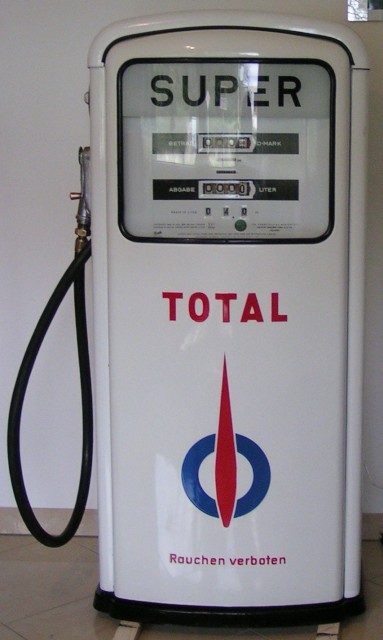
Schriftart altes "Total" Logo von 1955
ich suche die Schriftart vom Schriftzug "Total" der Beispielgrafik im Anhang.
Es handelt sich um eine Zapfsäule, die noch ca. im Jahr 1955 verwendet wurde.
Evtl. ist der Schriftzug auch eine Eigenkreation...
Total hat damals keinen waagerechten Schriftzug verwendet, daher ist der Schriftzug nur eine Anlehnung ans Logo.
1954
July 14 (Bastille Day) is chosen as the launch date for the "Super Carburant Total" brand. The first TOTAL logos emphasize its French nationality, with the name in red letters against a white background between two blue triangles. Marketing operations expand, and Total-branded products are introduced in different markets
1955
A gas pump logo expands on the French theme, with a red flame on a blue circle against a white background.
1963
The shape of blue-white-red symbol is softened, and the new logo is known familiarly as the "soap bar".
1970
Still in three colors, the logo is redesigned to express greater stability and strength (larger characters, horizontal design), rather than the earlier era’s more martial spirit of conquest (no more diagonals).
1982
A new trademark block is introduced, broadening the previously patriotic symbolism. It combines strength (bright red, powerful font), assertiveness (diagonal stripes) and friendliness (warm orange).
1991-1992
In June 1991, the Group takes the name of the brand that identifies it in more than 80 countries worldwide and in 1992, without changing its spirit, the trademark block is rejuvenated with more energetic lettering. The interior is simplified and given more drive by eliminating rounded edges, while horizontal lines are lighter and the space between letters is reduced. The stripes are narrower, opening up the brand and making it more readable. The colors are sharper.
2003
After the successful completion of two mergers with PetroFina and Elf Aquitaine, the Group is renamed Total in May 2003 with a new visual identity and a new logo.
Ok, das "Rauchen verboten" ist dann wahrscheinlich auch eine Eigenkreation?
Ah ok, das ergibt Sinn.
Dann muss es wohl nachgezeichnet werden (was mit dem krummen Bild nicht so einfach wird :-))
Das "Rauchen verboten" sah immer so aus, wie es der Schildermaler gezeichnet hat. Damals gab es keine Einheitlichkeit. Hier ein anderes Beispiel:
Kann man beispielsweise in Photoshop entzerren.